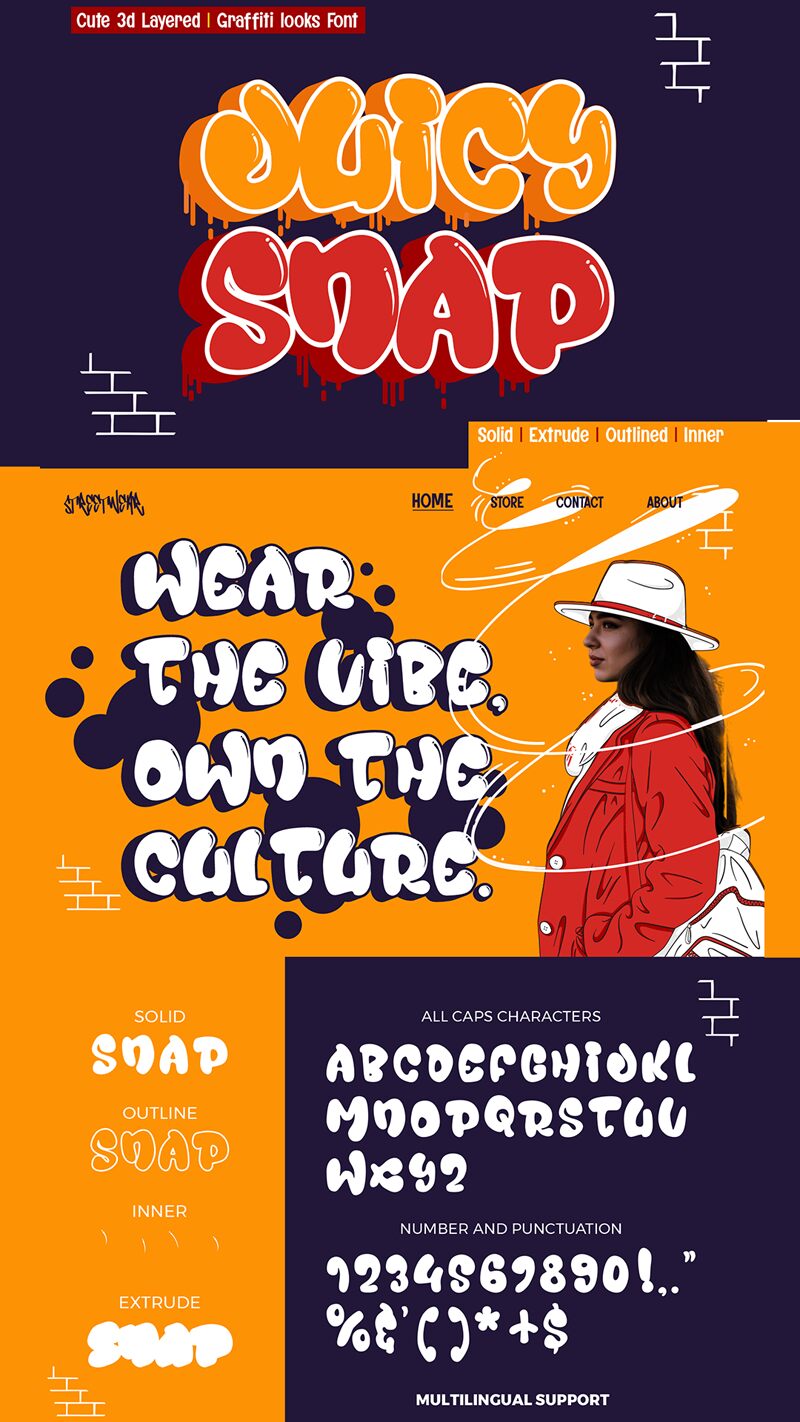
Písmo Juicy Snap Solid od Muhammada Panji Ramdhaniho (Sipanji x Figuree) přináší do rodiny Juicy Snap šťavnatý graffiti vibe. S robustními tvary připomínajícími kapky inkoustu působí písmena jako čerstvě nanesená barva, která ještě nestihla zaschnout. Písmena jsou široká a měkká, s hravými mezerami a stálým rytmem, který udržuje čitelnost i v tomto grafickém chaosu. Je to bezplatné graffiti písmo, které má dostatek stylu na to, aby na sebe strhlo pozornost, aniž by vytvořilo vizuální šum.
Použijte Juicy Snap Solid pro dodání výrazné osobnosti vašim streetwearovým logům, hudebním a festivalovým plakátům, sadám samolepek, skateboardovému či obuvnickému brandingu, miniaturám na YouTube, údernému merchi a hravým reklamám na sociálních sítích. Toto bezplatné písmo vynikne, když mu dáte prostor – zkuste ho ve velkém formátu a zbytek designu udržte jednoduchý. V popiscích ho zkombinujte s čistým, úzkým bezpatkovým písmem v verzálkách, aby Juicy Snap Solid zůstalo hlavní hvězdou.